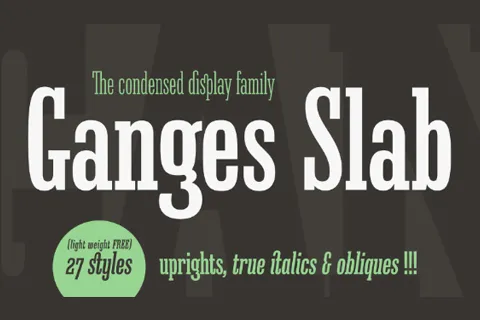
Descubra uma nova fonte para seus projetos de design editorial e layout! Introduzimos Ganges Slab Font Family criado por ROHH, uma família de tipo slab serif inspirada na tipografia de anúncios central europeia do final do século XIX. O Ganges Slab é perfeito para combinar com o seu par sans-serif chamado Ganges Sans. Esta fonte tem proporções compactas e formas de letras originais, tornando-se uma escolha ideal tanto para design editorial como para pequenos trechos de texto. Com sua proporcionalidade estreita, a Ganges Slab se destaca especialmente para aplicações que exigem um uso expandido, como cartazes e capas de revistas. Além disso, seu design atento às formas de letras torna-a uma excelente opção para projetos de identificação visual, logomarcas e embalagens. Ganges Slab também se destaca como fonte ideal para headlines em sites e livros digitais. Através da Ganges Slab Font Family, você pode trazer um toque único e atraente aos seus trabalhos gráficos!